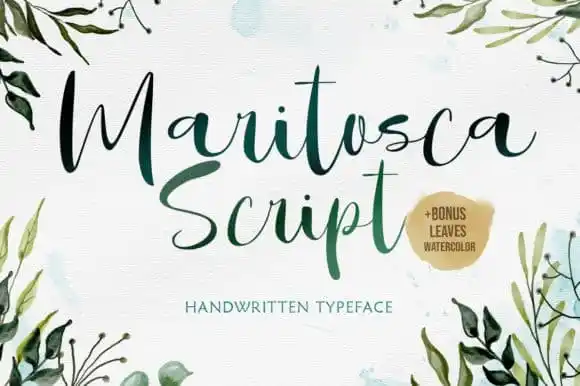
A Maritosca Script Font é uma elegante tipografia script que traz à vida um estilo sofisticado e delicado. Desenvolvida pela Letterhend, essa fonte captura a beleza classicamente chinesa do guache ao manter seu olhar contemporâneo e atual. Perfeita para aqueles projetos que buscam uma mistura de elegância com modernidade, Maritosca Script é o ideal escolha para revolucionar seus trabalhos em design. Adotá-la em sua próxima peça gráfica pode transformá-la em um elemento diferenciado, levando-a ao nível mais alto. Experimente a diferença da Maritosca Script e explore seu potencial sem precedentes.